Über FontFonter.com jede Website mit Webfonts ansehen
Seit Erscheinen der ersten 1250 Web-FontFonts im Februar 2010 (siehe auch: Heute ist Webfont-Tag) äußerten Webdesigner immer wieder den Wunsch nach einer Testseite für diese bildschirmoptimierten Schriften. Es hat uns etwas beschäftigt, weil FontShop kein weiteres »Fontlabor« einrichten wollte, sondern eine Testumgebung, die allen Live-Situationen gerecht wird und praktisch jede typografische Stellschraube berücksichtigt. Warum nicht auf existierender Webseiten einen Schriftwechsel durchführen. Gesagt, getan!
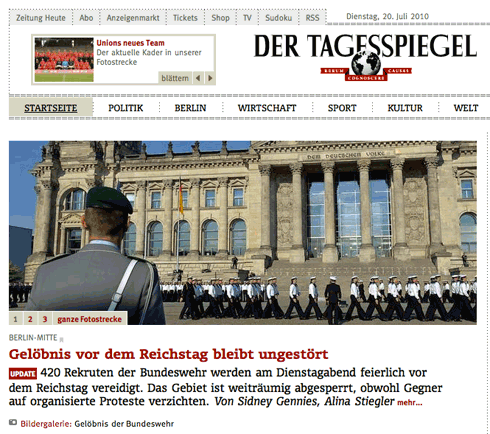
Die Homepage des Tagesspiegel – statt in Ariel und Verdana hier in FF Olsen Web
Nun ist sie da, die Experimentierkammer FontFonter, der schnellste und einfachste Weg, um Webfonts auf bestehenden Websites Probe zu fahren. Wer seine Lieblingsseite mal in einer anderen Schrift lesen möchte oder für ein Projekt in Arbeit ein paar Fonts durchspielen möchte wird www.fontfonter.com sofort lieben. Das Portal entstand in Zusammenarbeit mit Tim Ahrens (Just Another Foundry) und erlaubt zur Zeit das Einspielen von 25 verschiedenen Web-FontFont (darunter auch die neue FF DIN Round), wobei sich Serif- und Sans-Schriften getrennt voneinander austauschen lassen. Die Auswahl der Schriften wird in den kommenden Tagen erweitert.
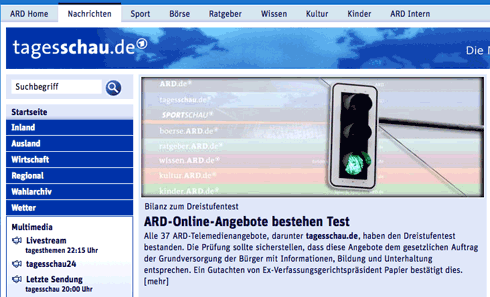
Die Homepage des Tagesschau – ausnahmsweise mal in der Schrift FF Unit Web
FontFonter lief in den vergangenen 14 Tagen als Private-Beta, was zu einer Menge interessanter Verwandlungen führte. Vier davon sind auf der Startseite als Anregung zu sehen: die Homepages der New York Times, von Twitter, Digg und Google. Viele von uns haben gleich die eigenen Blogs unter die Lupe genommen, um den Abschied von den allgegenwärtigen Georgia und Verdana vorzubereiten. Andere suchten schlicht (die oben bereits zitierten) Font-Testseiten auf, um sich einigen Web-FontFonts analytisch zu nähern … hier zum Beispiel der FF Quadraat Web auf Tim Brown’s Web-Font-Specimen-Seite :-)
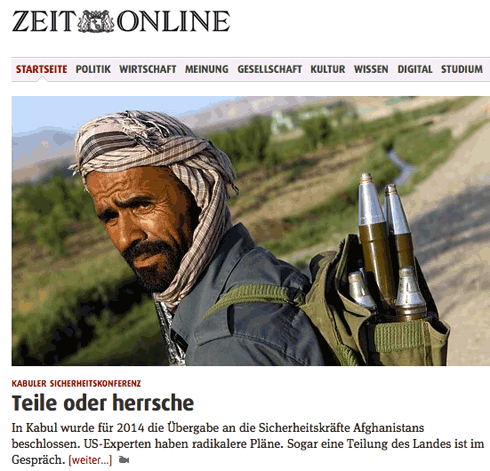
Die Homepage der ZEIT – versuchsweise gesetzt aus FF Dax Web und FF Meta Serif Web
Wieso macht Fontshop USA immer die innovativeren Sachen?
„Ohne Klimaanlage wären die USA keine Weltmacht“ (Die Welt, 14. Juli 2010)
Da ist was dran.
Web-FontFonts als Einzelschnitte downloaden: Der Fehler ist behoben, in wenigen Stunden ist alles live …
Thema Amis: Warum so bescheiden … die Technik hat Tim Ahrens entwickelt (D), die Web-FontFonts sind Made in Germany. Die Didaktik kommt aus den USA.
Nein. Der FontFonter (nicht notwendigerweise die Web FontFonts) funktioniert derzeit nicht auf iPad & Co, Internet Explodierer und Opera.
Danke. Ärgerlich das man derzeit zig verschiedene Formate einbinden muss um sämtliche Browser zu bedienen.
Ich hoffe das sich ein Standard in absehbarer Zeit etabliert.
Florian, es sind nicht zig Formate, sondern zwei: .woff und .eot
Hut ab!
sehr schicke idee. aber, großes hmm. bei aller begeisterung für fonts – mich überzeugen die dort eingesetzten Schriften nicht. auf meinem 15″ 1680×1050 mac sieht das alles sehr matschig aus, unproportional in weißraumanteil und die buchstaben zu fett. ich weiß, das ist alles noch am anfang, aber bildschirmfonts sind scheinbar doch nicht ganz umsonst anders als webfonts. da muss noch ganz schön nacharbeit bei den schriften gemacht werden, wenn man eine vernünftige print—>web variante haben will. (betrifft nicht nur fontfont fonts, sondern sehr vieles, was gerade so als webfont rumgeistert.)
seb,
an Deinem Mac ist es egal, wie viel Arbeit noch in den Font gesteckt wird; Er liest das Glyphlevel-Hinting nicht aus und kocht sein eigenes Süppchen, was die Bildschirmdarstellung betrifft.
Jürgen,
schön wär’s! Damit erreicht man ja leider bisher nur den neuen Firefox und den IE. Aber WOFF wird sich gottseidank bald durchgesetzt haben.
Da stimmt doch was nicht. Die Schriften kommen (auf Safari) als TTF-Dateien von ffonts.justanotherfoundry.com, während die „Web-Fontfonts“ doch nur aus WOFF und EOT bestehen. Es ist zwar schön, dass es so mit Safari funktioniert, aber wo ist jetzt der Zusammenhang zu den „Web-Fontfonts“?
@Jürgen.
Ich glaube da musst du nochmal ein wenig genauer recherchieren. ;)
Es ist nur nur .woff und .eot.
Vom Ding her musst du derzeit noch gut 4 Formate via Font-Face einbinden um wirklich alle Browser zu unterstützen.
Das wären zum einen .eot was im Inter Explorer Verwendung findet, vor allem ältere IE’s benötigen diesen Dateityp.
Dann .woff, als wohl zukünftiger Standard für moderne Browser (Firefox 3.6, Safari, Chrome etc)
Für iPhone und iPad benötigst du .svg, auch ein Vector Format. Wie schon oben beschrieben können diese Geräte nur mit .svg arbeiten.
Zum Schluss gibt es noch das aus der Printweltbekannte .ttf und .otf. im Normalfall aber meistens .ttf.
Wie du siehst, von „nur“ 2 Formaten sind wir wohl noch etliche Monate entfernt. ;)
@Florian
Ich hatte „nur zwei Formate“ so verstanden, dass die Web-Fontfonts mit eben nur diesen beiden Formaten „auskommen“, da sie andere Voraussetzungen ignorieren. Und nicht, dass hier jemand der Meinung sei, es gäbe nur WOFF und EOT.